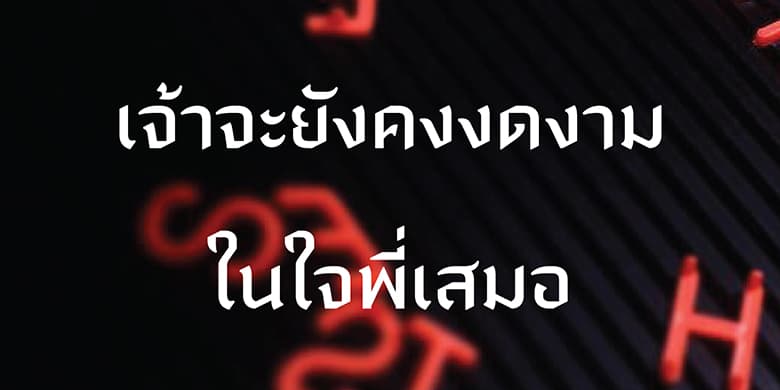
Naresuan
品牌:Cadson Demak设计师:Chorong Kim发行时间:2009字库编码:Unicode分类:无衬线体字体属性:
此种字体最初的构思是用于电影媒体,该字型的吸引力在于字母的形式是由韩国设计师诠释。采用字母形状的角度来观察胜过于从语言范畴的角度来观察。通过选用由使用切割笔头书写而引起的色带结构,并通过设定书写方式以取得相同的结果。所得到的结果使得泰文字母产生出当代的形式并使理想中的泰国文字风彩得以保存。
ตัวอักษรสำหรับภาพยนต์ ตำนานสมเด็จพระนเรศวรมหาราช ถูกนำมาปรับปรุงใหม่โดยทีมงาน คัดสรร ดีมาก ให้มีความลงตัวมากยิ่งขึ้น